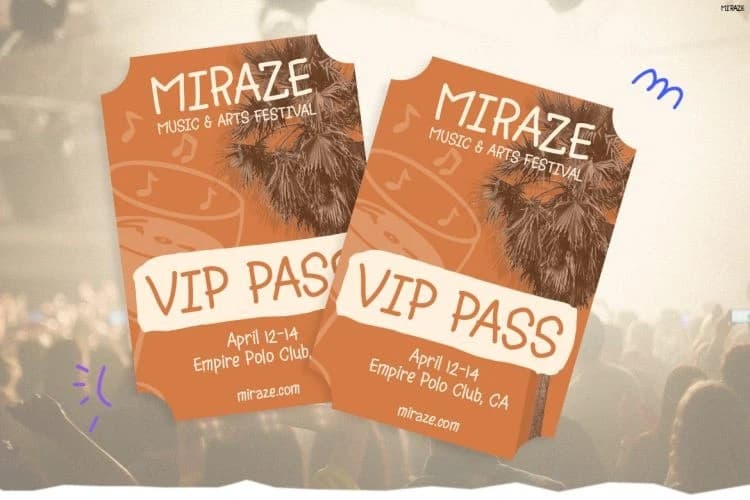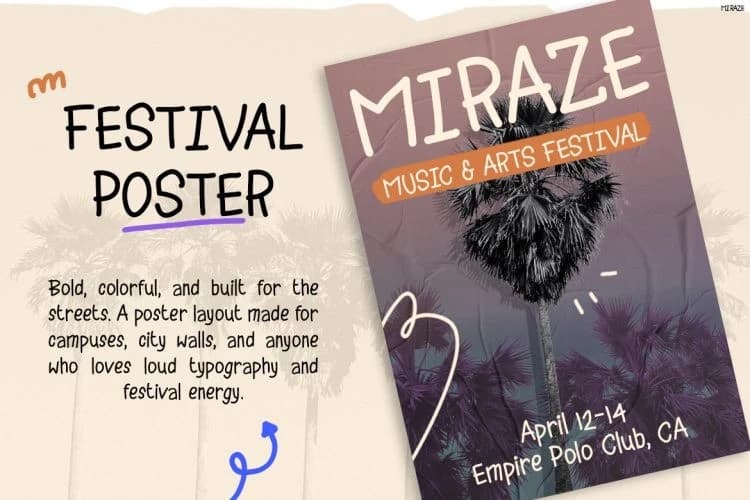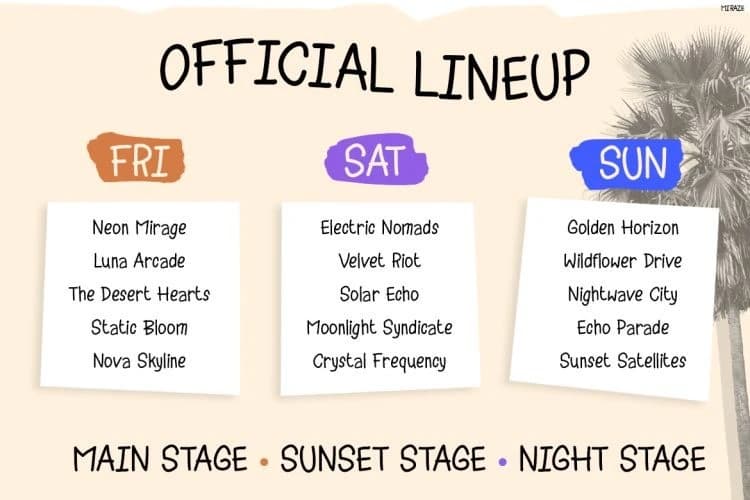
Miraze Oyuncu Yazı Tipi
Miraze Playful Font, müzik festivalleri, çöl maceraları, yaratıcı özgürlük ve genç ifadeden ilham alan cesur bir el yazısı gösterim yazı tipidir. Enerjik çizgilerle ve doğal olarak kusurlu harflerle tasarlandı.
Miraze Playful Font, müzik festivallerinden, çöl maceralarından, yaratıcı özgürlükten ve gençliğin ifadesinden ilham alan cesur bir el yazısı gösterim fontudur. Enerjik çizgilerle ve doğal olarak kusurlu hatlara sahip olarak tasarlanmıştır.